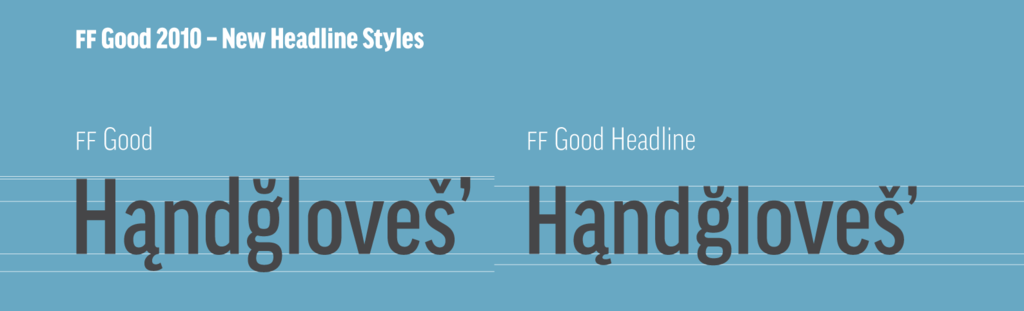
schmale Grotesk im Retro-Style gesucht
Ich suche auch gerade eine schmale Grotesk für Headlines in einem Magazin. Allerdings sollte die Schrift nicht ganz so verspielt sein sondern eher etwas Retro wie beispielsweise die Founders Grotesk Condensed oder X-Condensed. Hat noch jemand Tipps in dieser Richtung?
Zum 80. Geburtstag von Jean Luc Godard Ende 2010 gab es die Schrift »Jean Luc« gratis zum Downloaden. Ich weiß nicht, ob es sie immer noch (eventuell käuflich zu erwerben) gibt, aber von der Art her könnte sie vielleicht für Dich interessant sein, Microboy? Ich fürchte allerdings, wenn mich die Erinnerung nicht trügt, gibt es die Schrift nur in Versalien …
Danke für die ganzen Tipps. Momentan schwanke ich noch zwischen Tablet Gothic und Founders Grotesk.